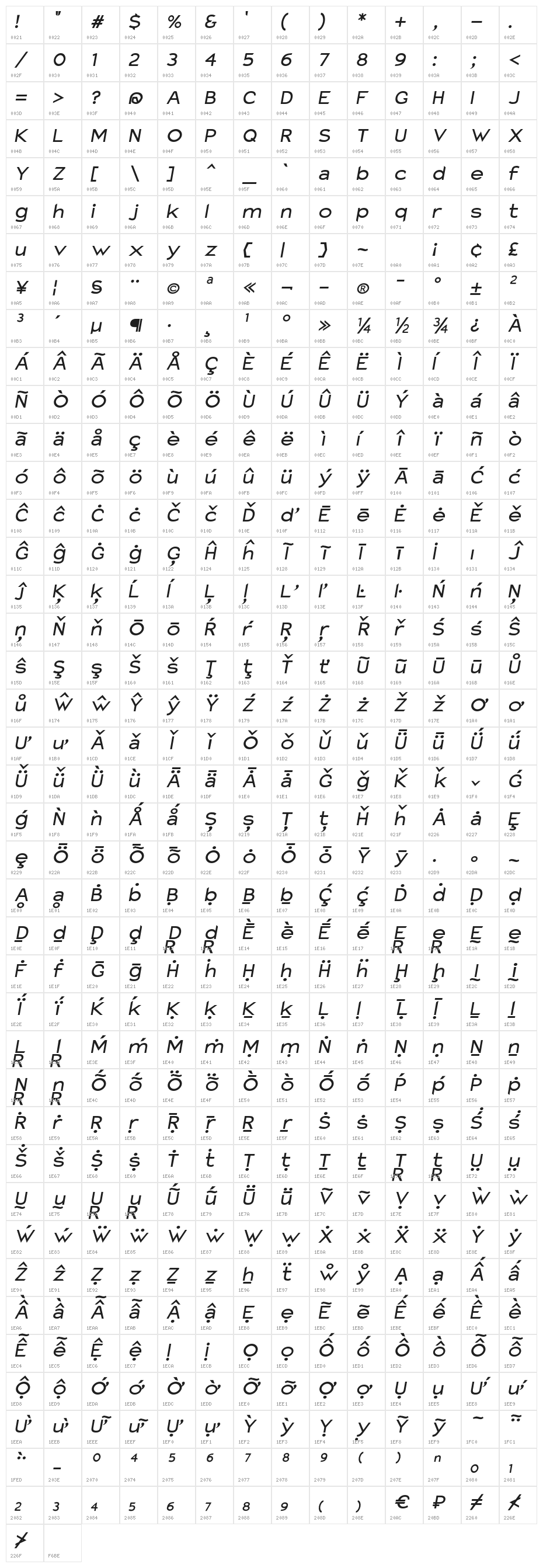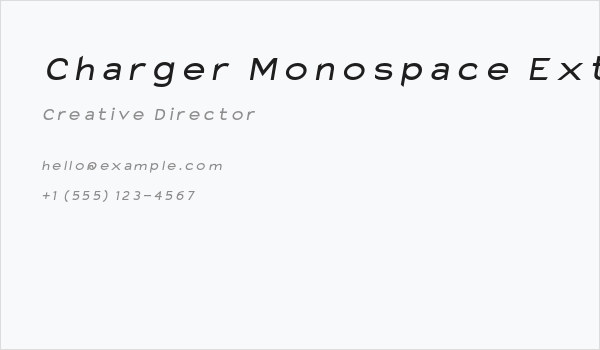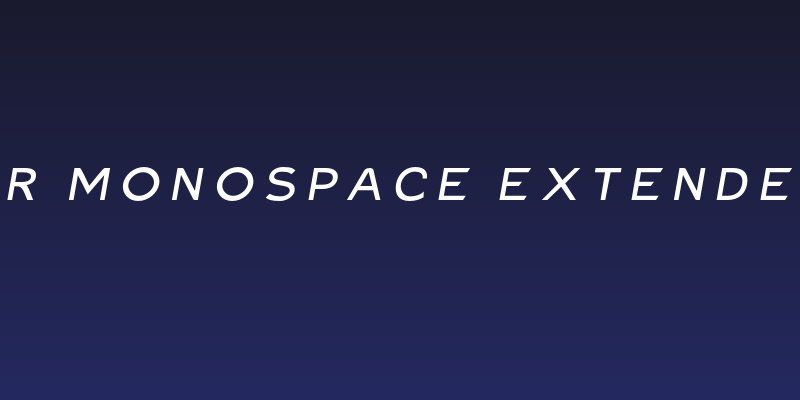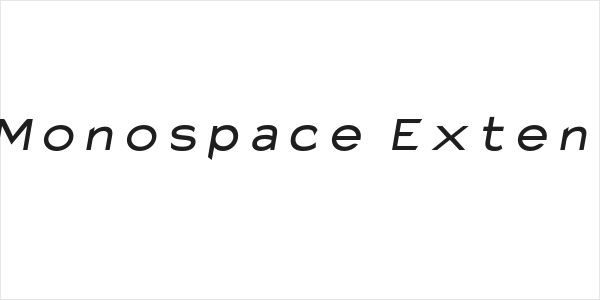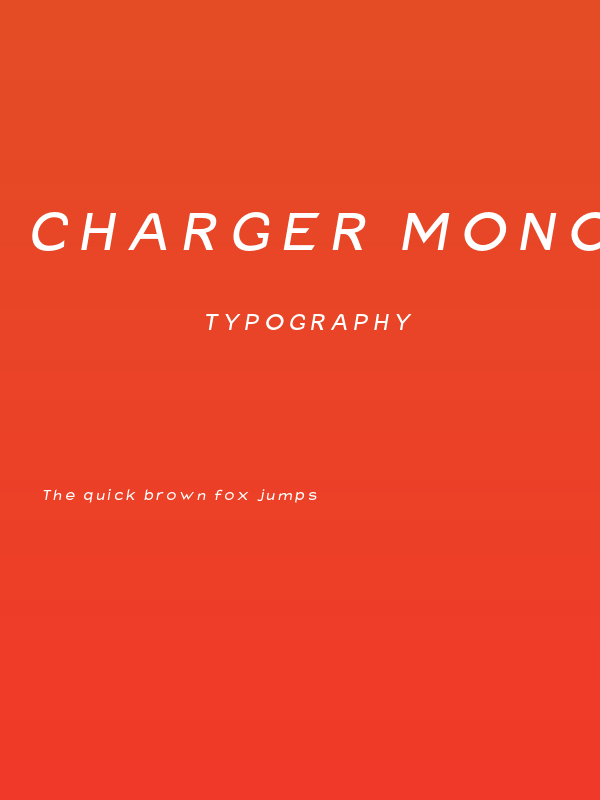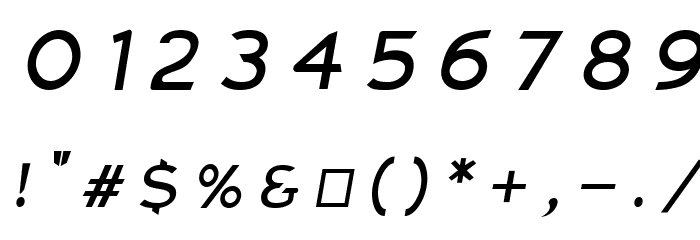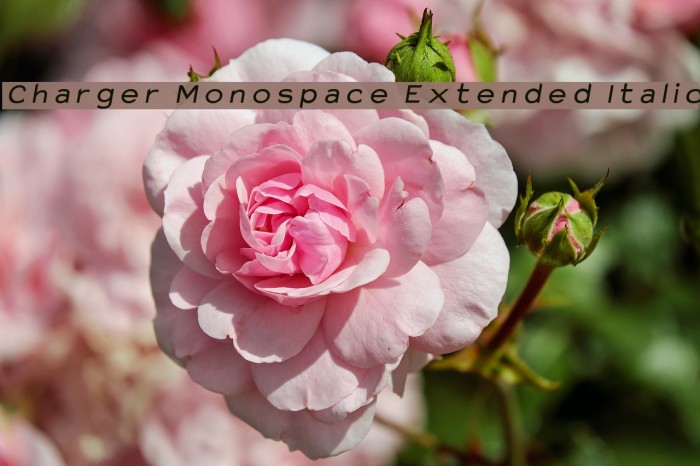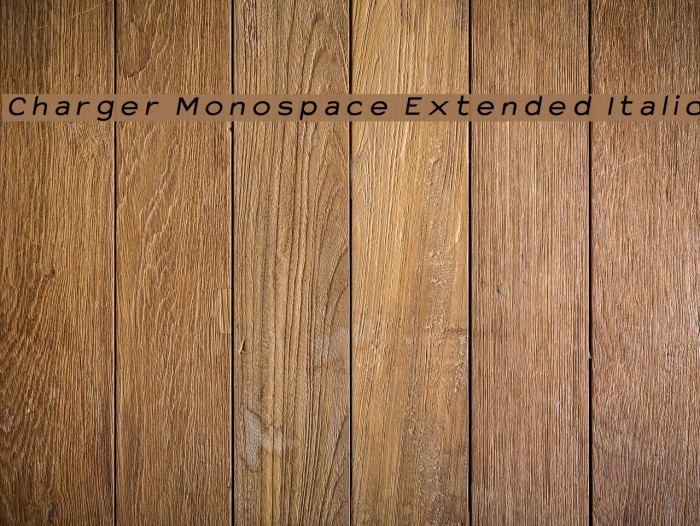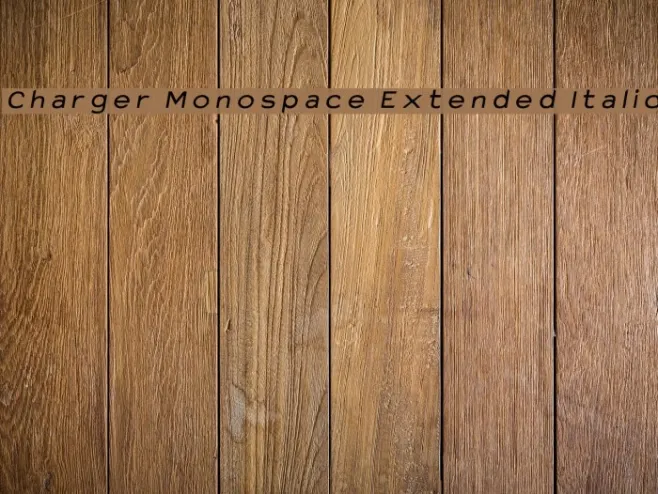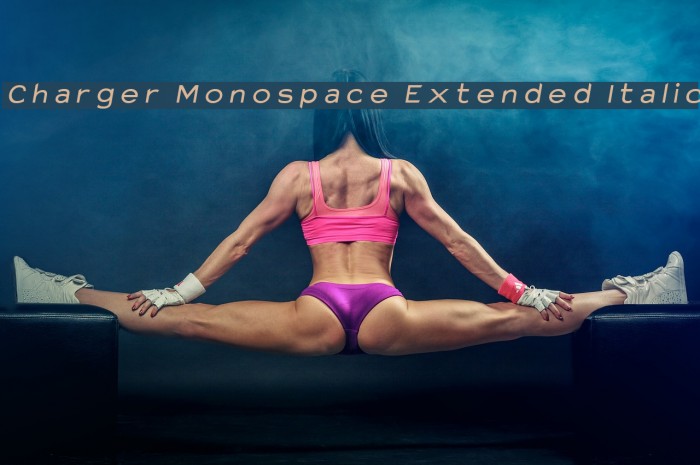
Charger Monospace Extended Italic Font
| Projets proposés | Ideal for coding environments, technical documentation, modern branding, and digital interfaces. |